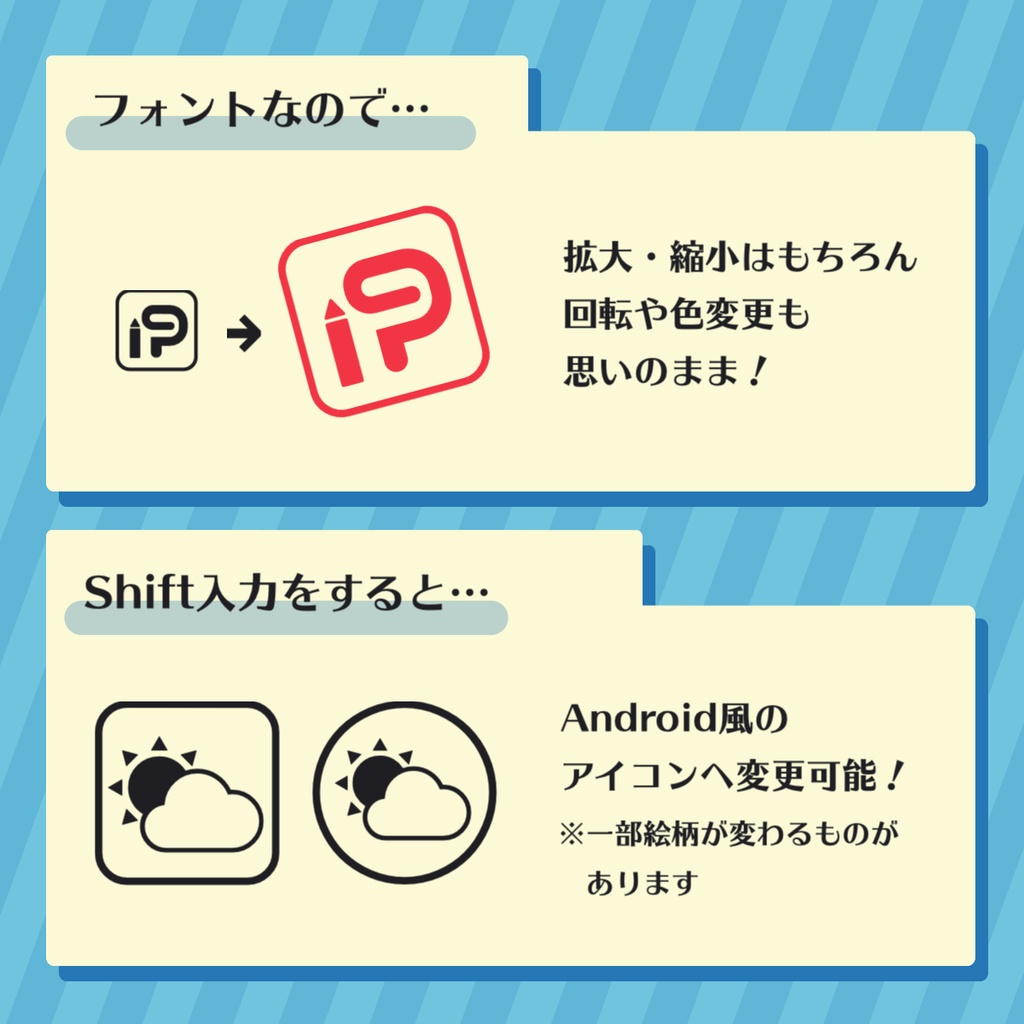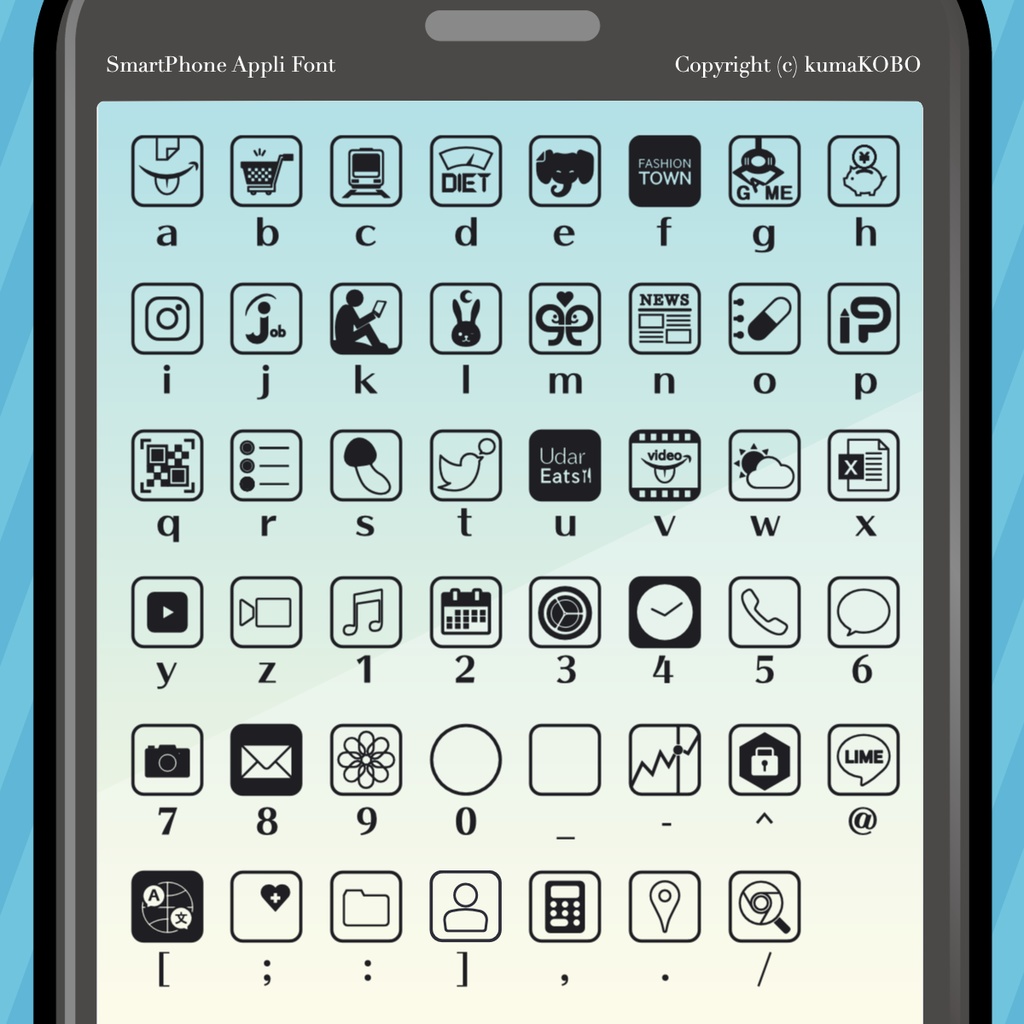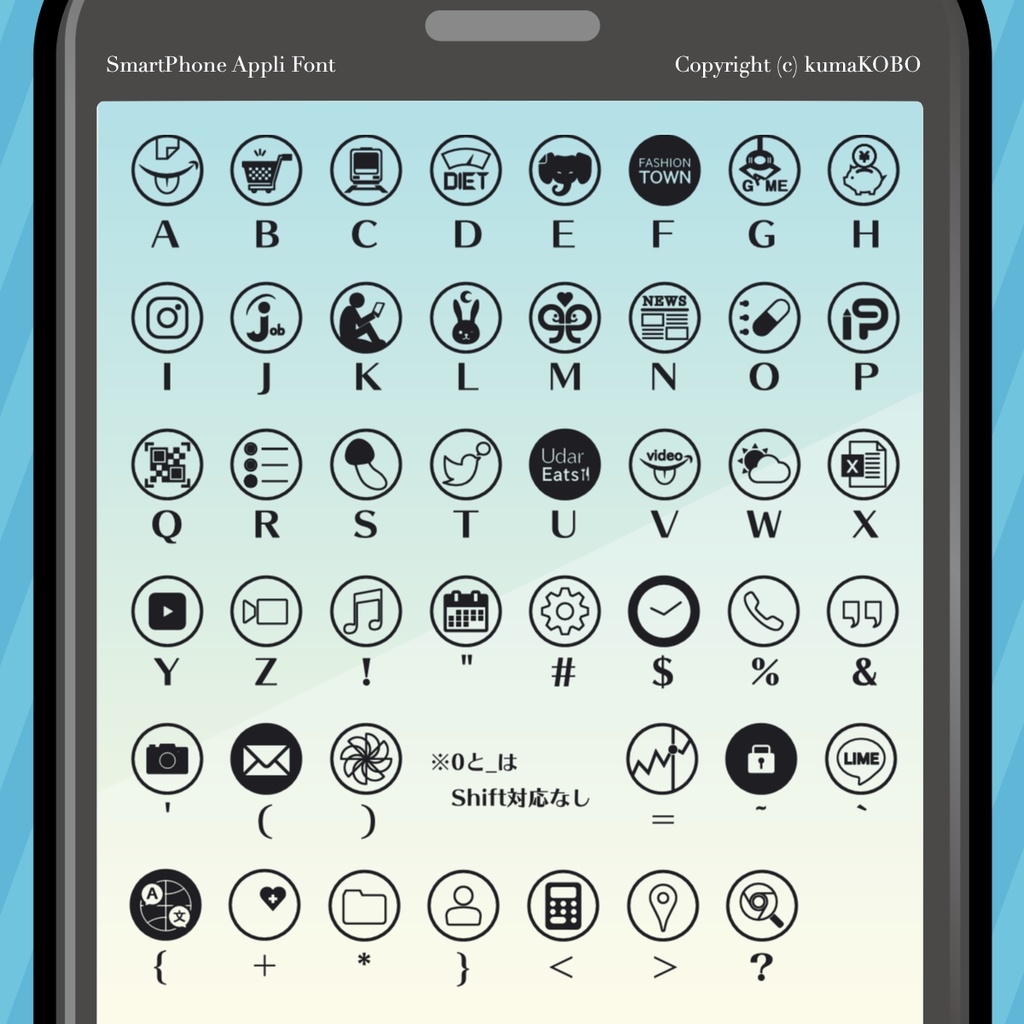
【フォント形式素材】スマホアプリフォント
キーボードを打つだけで簡単にスマホのホーム画面が作れる画期的なフォントアイコン素材です。 同人誌等の漫画でスマホ画面を描く作業時間を短縮する目的で作られました。それ以外の用途での使用もご自由にどうぞ(※個人利用に限り)。 そのままの入力でiPhone風の四角いアイコン、Shift入力でAndroid向きの丸いアイコンになります(一部デザインが異なるものもあります)。また、作成者がiPhoneしか使った事がないため、Androidの方には馴染みのないアプリがあるかもしれませんがご了承ください。 1~9,記号(アンダーバーを除く):主に標準アプリ、LI●Eなど大体の人が入れていそうなアプリが入っています。 a~z,A~Z:主にアプリストアでDLするアプリが入っています。それとなくアルファベットに対応したアプリが出てきます(A:a●azon風、B:BUY(買い物)など) 0,_(アンダーバー):空白のアイコンが入ります。オリジナルのアイコンを描き込みたい時に。 ※¥,|はフォント作成ソフトの関係上、割り当てできなかったので何も入りません 数字と記号のみが入ったお試し版も用意しております。 フォントがPCに対応しているか、素材が作品の雰囲気に合うかどうか確認する際にお使いください。